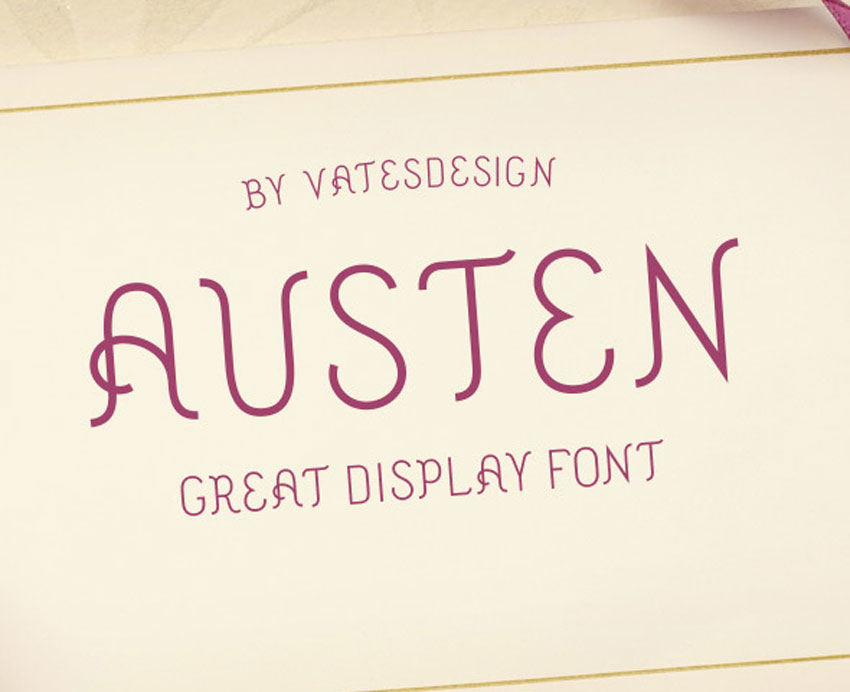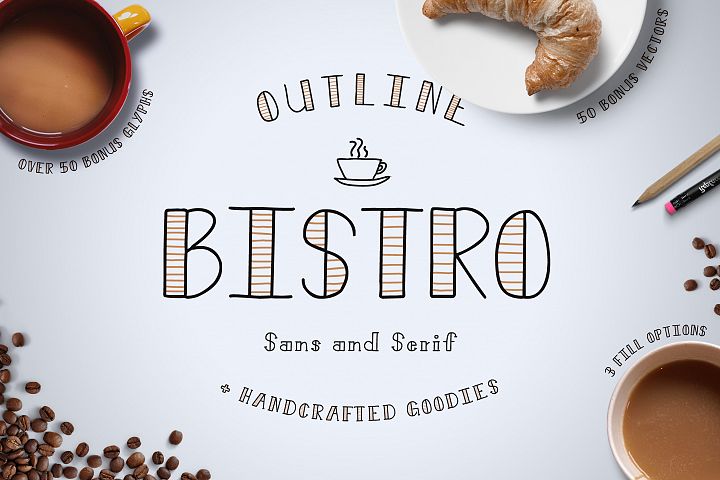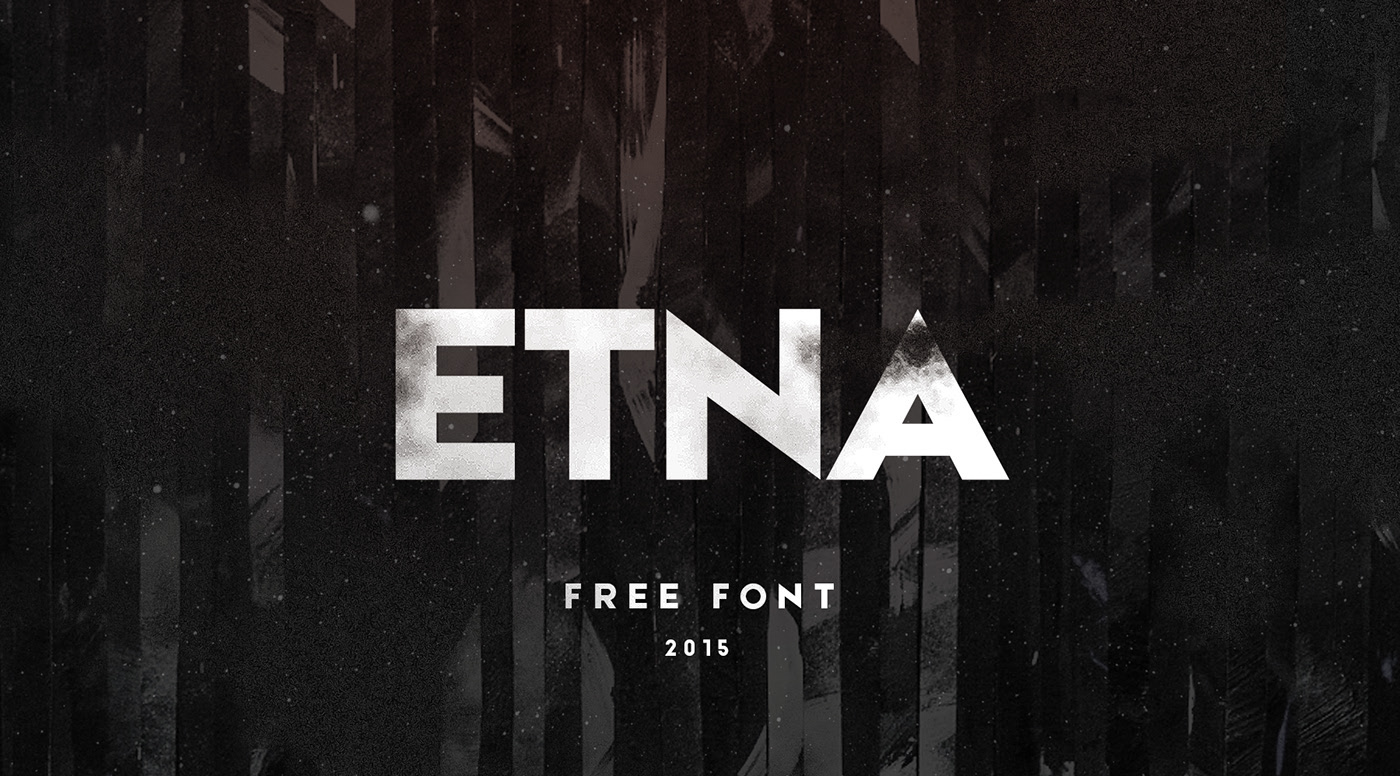
Tidak masalah jika kamu logo disainer , graphic disainer, ataupun web disainer, kali ini kita akan membagikan beberapa font gratisan yang bisa kamu jadikan bahan untuk log design kamu selanjutnya.
Pada list font kali ini terdiri dari 3D fonts, uppercase, lowercase, angled dan banyak tipe font lainnya, semuanya memiliki keunikannya sendiri sehingga sangat pas untuk di jadikan logo atau print design. Ok langsung aja kita cekidot gais.
Sudah saatnya kita update list font keren untuk logo terbaru.
Font yang keren punya beberapa kretirea khusus. Diantaranya:
Kerning, kerning adalah jarak antara satu caracter font dengan yang lainnya. Pastikan font tersebut memiliki kerning yang sesuai sehingga font terlihat bagus dan keren.
Consistency. Pastikan font tersebut memiliki style yang sama di setiap characternya. Dari A - Z 0 - 9.
Balance. Adanya keseimbangan antara tebal dan tipis font menjadi sebuah standar dimana font tersebut bagus dan keren.
Legibility. Ini maksudnya, font itu harus masih bisa dibaca saat dibuat besar ataupun kecil.
Kami berikan 2 font update yang tidak kalah menarik dan pastinya bisa kamu coba secara gratis.
Nah jika sebelumnya kita sudah share beberapa font gratis untuk quotes, kita akan mengupdate list font keren untuk logo. Diantaranya:
1. Manifesto
List pertama kita ada font keren bernama Manifesto.
Font ini keren digunakan dalam logo kamu. Font yang tidak terlalu tebal dan juga tidak terlalu tipis bisa membuat logo kamu semakin stand out dari yang lainnya.
2. Etna
List kedua, yaitu Etna. Font ini tebal dan tegas, cocok untuk digunakan di berbagai keperluan termasuk logo.
3. Shintya Typeface
Shintya Typeface adalah font yang bergaya caligraphy dengan tulisan yang melengkung-lengkung dan cantik tentunya. Font ini cocok untuk design logo tentang fasion ataupun kecantikan.
4. Austen Display Font
Austen Display Font adalah font klasik yang sangat berkarakter. Jika kamu butuh font keren untuk logo kamu yang berbeda dengan yang lainnya, font ini recomended banget.
5. Voyageur
Voyageur adalah font yang cukup unik. Termasuk ke category handwriting, font ini bisa kamu gunakan jika ingin membuat sebuah logo dengan style yang kurus-kurus.
6. Bistro
Bistro salah satu font favorit saya untuk membuat logo makanan. Termasuk ke dalam tipe handcrafted font, jadi memberikan kesan yang tegas dan unik untuk logo kamu.
7. AILERON
AILERON salah satu font klasik dengan huruf yang tipis dan lengkungan yang halus. Font ini memberikan kesan yang santai pada logo kamu.
8. QANELAS SOFT
Qanelas Soft adalah font san-serif dengan design yang modern dan tegas. Kamu bisa gunakan font keren ini untuk membuat logo yang bersifat tegas dan modern.
9. Khalif Irsyad
Font karya dari Nirmala Visual ini adalah tipe brush font. Seperti tulisan yang dibuat menggunakan kuas. Sangat cocok untuk membuat logo klasik ataupun membuat text caption di gambar.
10. RUMBLEBRAVE
Font karya dari Alit Design ini khusus untuk kamu yang suka dengan font retro. Sangat cocok untuk untuk membuat logo-logo yang beraliran retro dan juga bisa digunakan sebagai pilihan font untuk caption difoto yang instagramable.
Duma Font
DUMA termasuk tipe font sans yang mempunyai karakter kaki-kaki yang panjang dan bentuk yang luas. Masing-masing karakter dibuat di Illustrator menggunakan bentuk dasar geometri.
Font gratis untuk logo
Reckoner Font
Desainer dari font ini terinspirasi oleh font bertipe sans serif seperti Bebas Neue, Alegre Sans & Dharma Gothic. Reckoner ini gratis untuk penggunaan secara komersial ataupun personal.
Font gratis untuk logo
Silent Lips Free Font
Font yang satu ini adalah font experimental hasil dari banyak percobaan. Dengan design-nya yang ramping, sangat cocok di gunakan dalam print atau web design.
Font gratis untuk logo
Aaram Free Font
Aaram adalah font family yang unik, yang terdiri dari 6 style yang dapat dipilih. Walaupun Aaram didesain untuk desain layar, tapi sangat keren juga untuk print desain.
Meticulous Ariel Free Font
Meticulous Ariel adalah typeface baru yang terinspirasi oleh dunia fashion. Meticulous Ariel Typeface terlihat sangat bagus jika digunakan di majalah fashion dan merek merek terkenal. Font ini mempunyai sentuhan eropa klasik lo gais.